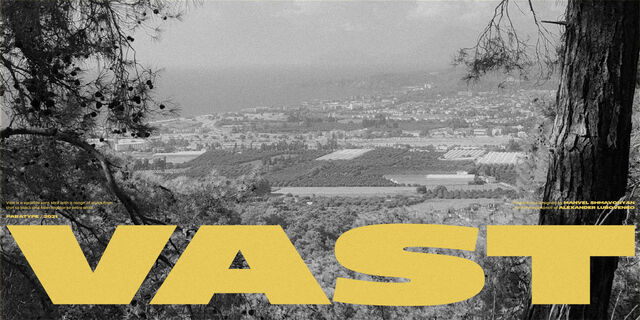
Vast — многофункциональный гротеск с диапазоном начертаний от сверхсветлого до сверхжирного и от нормального до сверхширокого. Характер этого шрифта одновременно серьёзный и дружелюбный. Регулярное начертание хорошо работает в тексте, а светлые, жирные и широкие варианты отлично подойдут для заголовков и брендинга. Vast будет «на своём месте» в любом месте, где нужно внимание и уважение к читателю, от супермаркета до поликлиники.
Шрифт разработан Манвелом Шмавоняном при участии Александра Любовенко и выпущен компанией Паратайп в 2021 году.